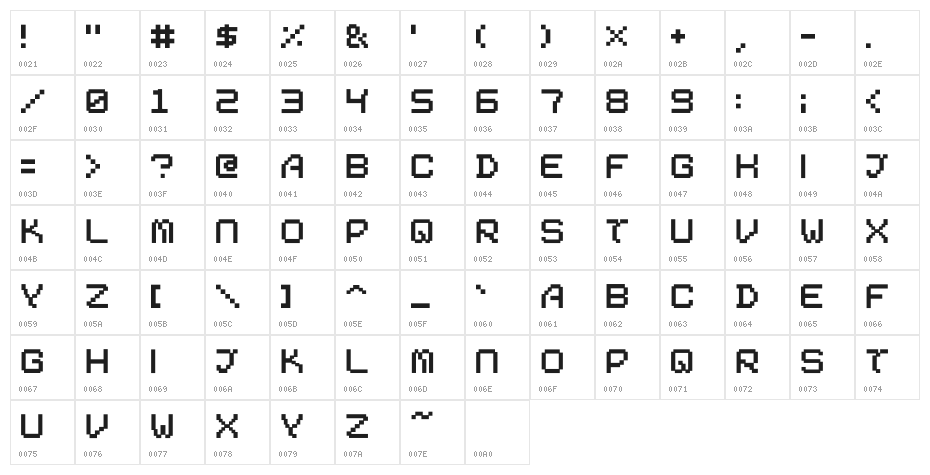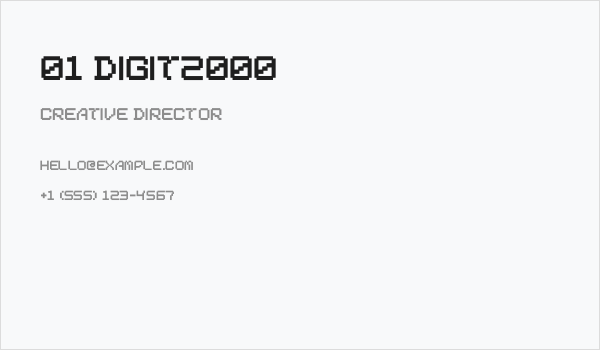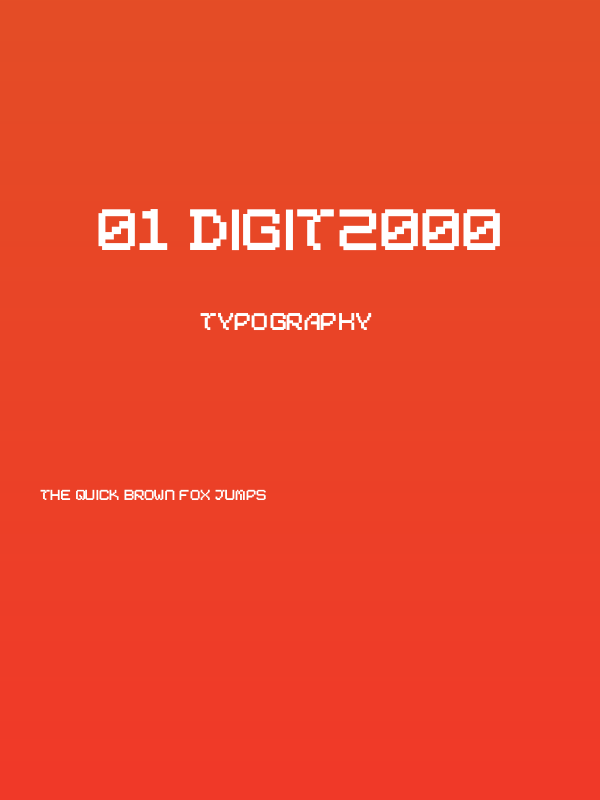
01 Digit2000 Font
| Stile generale | Retro, Digital |
| Caso d'uso | Logos, Digital displays, Video game graphics |
| Progetti proposti | Ideal for tech-themed designs, retro video game graphics, digital displays, and any project seeking a nostalgic, digital aesthetic. |